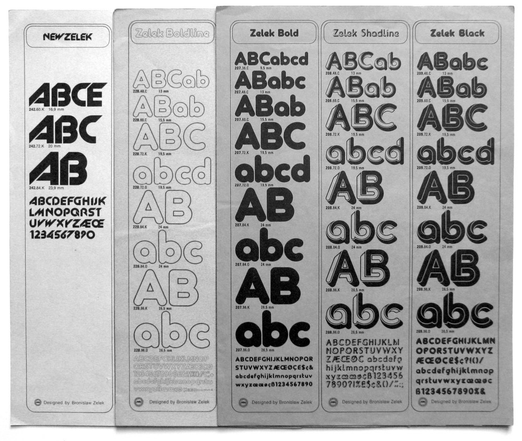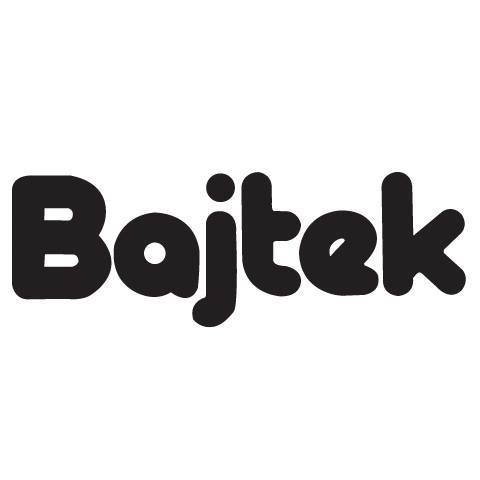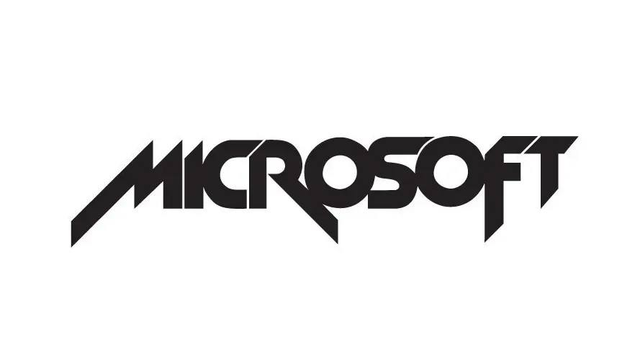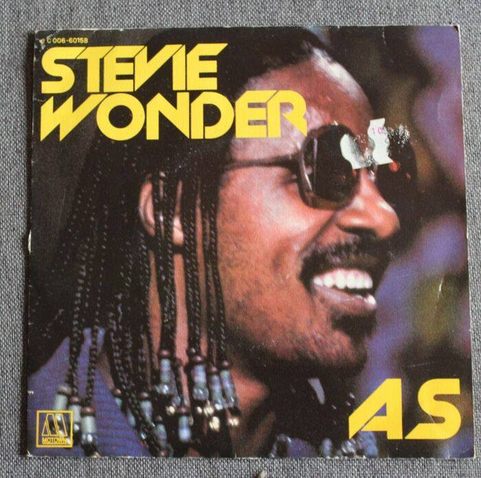
Pamiętacie „Bajtka”? A zastanawialiście się kiedyś, jakim krojem pisma złożone było jego logo?
Bo ja nie, ale właśnie odkryłem odpowiedź na to pytanie i myślę, że jest warta rozpropagowania. To Zelek Bold projektu Bronisława Zelka.
Kroje Zelka były najpopularniejszymi poza Polską produktami polskiej myśli typograficznej z epoki przedcyfrowej. Krojem New Zelek złożone było m.in. logo Microsoftu z lat 1980–1982 i okładka jednego z albumów Steviego Wondera!
Kylläpäs ihmettelin tätä suomalaiselta kuulostavaa paikannimeä Havaijilla (vrt. Hanasaari ja Kallio Helsingissä). Sitten huomasin, että Google Maps näyttää heittomerkin jälkeisen kirjaimen virheellisesti isona ja paikannimi onkin oikeasti Hanaka'ilio. Samasta syystä vieraskieliset kirjoittavat Ievan (ievan) polkan usein muodossa Levan polkka.
Typografiaa Intiasta: Blaft Publications -pienkustantamo kerää joukkorahoitusta India Street Lettering -valokuvakirjalle. Komean näköinen julkaisu! https://www.kickstarter.com/projects/blaft/india-street-lettering-a-book
Erään firman sivuilla otsikoissa oli käytetty fonttia, joka herätti mielenkiinnon.